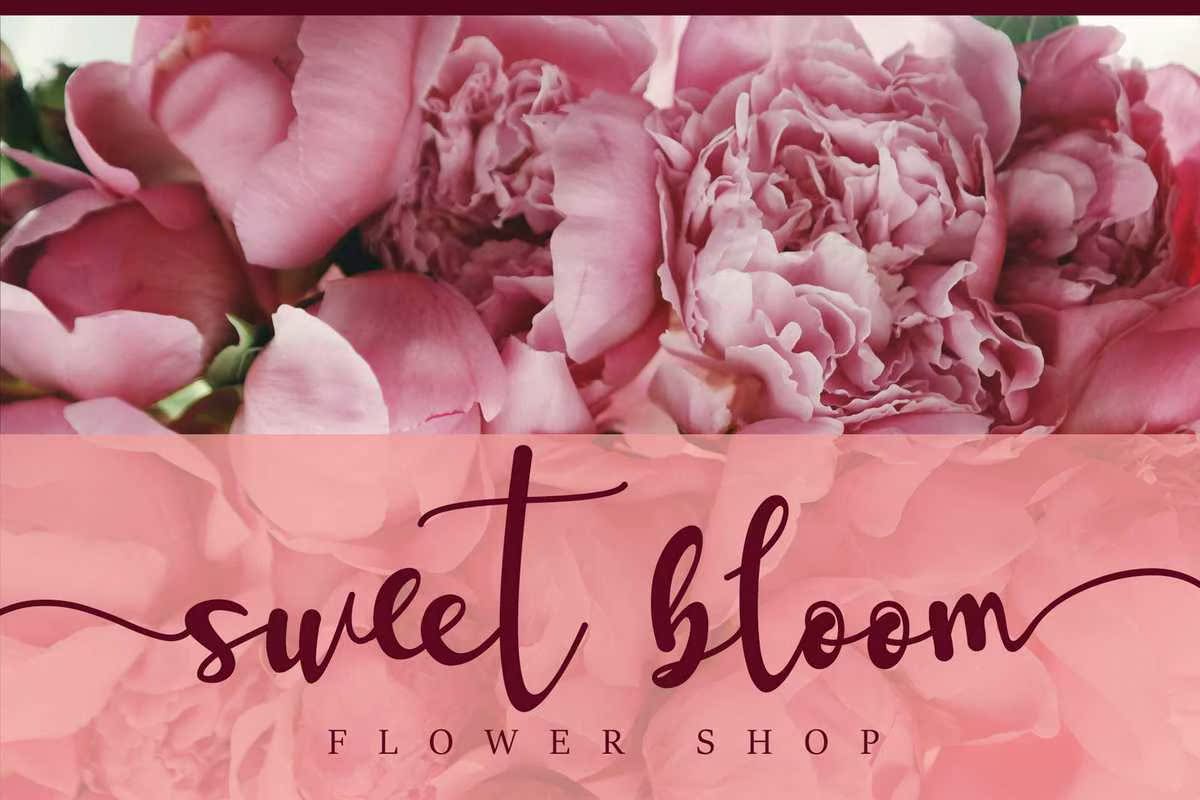
Lovelli是一种通用字体和现代字体。它将显示您的徽标、品牌、标题、短文本或任何项目所需的字体。此字体是经过编码的,意味着您可以访问这些字体和Swashease!爱上它令人难以置信的全能风格,并用它来创造壮观的设计!Lovelli是一种通用字体和现代字体。它将显示您的徽标、品牌、标题、短文本或任何项目所需的字体。此字体是经过编码的,意味着您可以访问这些字体和Swashease!爱上它令人难以置信的全能风格,并用它来创造壮观的设计!